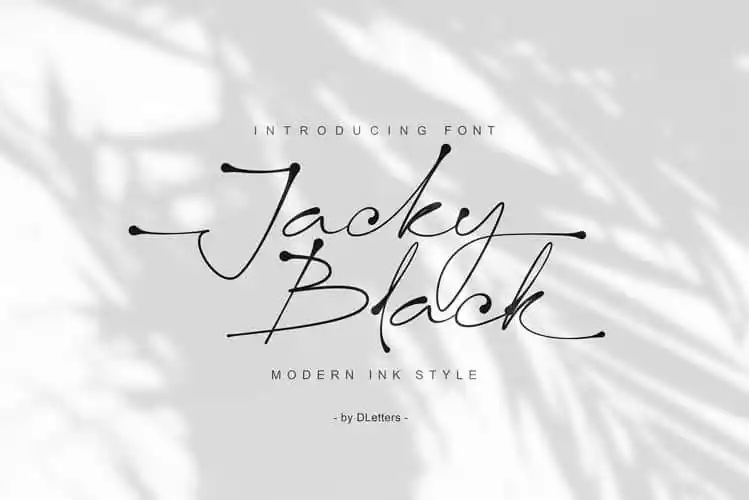
Jacky Black Handwritten Font – Download Grátis
A Jacky Black Handwritten Font é uma ótima adição para quem busca personalidade e elegância no design editorial. Esta tipografia em estilo escrita a mão traz um toque único à sua identidade de marca, oferecendo uma paleta completa de letras maiúsculas e minúsculas, números e marcadores de pular parágrafo. Desenvolvida pelo designer DLetters Std., esta fonte é projetada para apresentar a essência natural do escritor em cada caractere, enquanto mantém o aspecto elegante e exclusivo. Perfeito para quem quer incorporar um toque único à suas criações, seja em cartazes de comunicação ou em design editorial, a Jacky Black Handwritten traz uma sensação agradável de autenticidade e naturalidade ao seu trabalho. Com seu estilo próprio e leve, essa fonte oferece uma maneira divertida de dar um toque especial à sua escrita, garantindo que seja notada no meio de qualquer design. Seja para nomes ou headlines, esta fonte proporcionará o charme certo em qualquer projeto editorial. Não perca a chance de trazer mais vida e personalidade aos seus trabalhos com Jacky Black Handwritten Font.